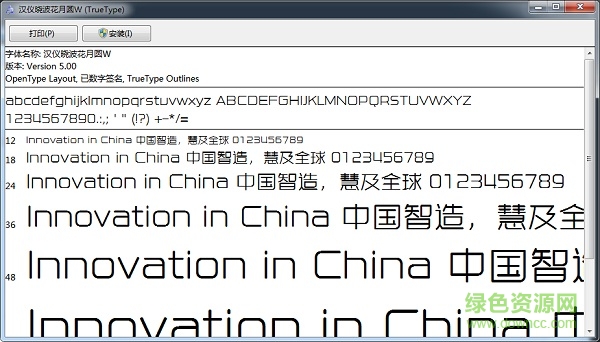
漢儀曉波花月圓字體
漢儀曉波花月圓體是一個(gè)可以支持win7、win8等主流系統(tǒng)環(huán)境下安裝使用的電腦字體應(yīng)用。這款字體外形美觀,字體看起來非常纖柔規(guī)整??梢宰顬槊佬g(shù)設(shè)計(jì)字體使用!歡迎來綠色資源網(wǎng)下載安裝。
漢儀曉波花月圓字體筆觸較為纖細(xì),書寫端正,能夠應(yīng)用于文本裝潢、信息展示、網(wǎng)頁設(shè)計(jì)、篆刻制模、數(shù)據(jù)制作、裝潢設(shè)計(jì)、計(jì)算藝術(shù)設(shè)計(jì)、視覺設(shè)計(jì)、字帖等一切合法應(yīng)用場(chǎng)景!
漢儀曉波花月圓字體預(yù)覽:
漢儀曉波花月圓體